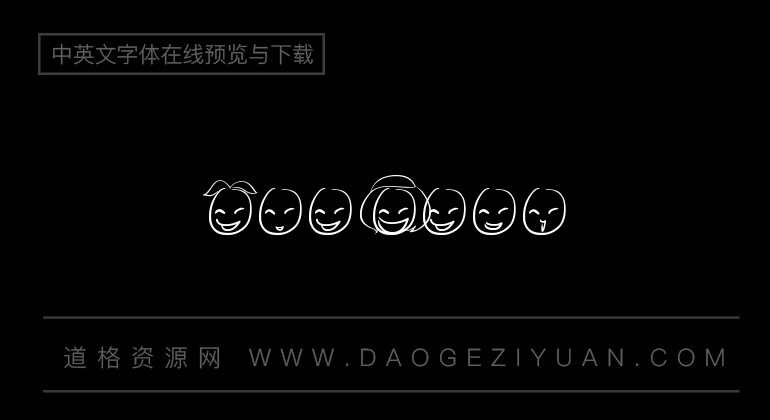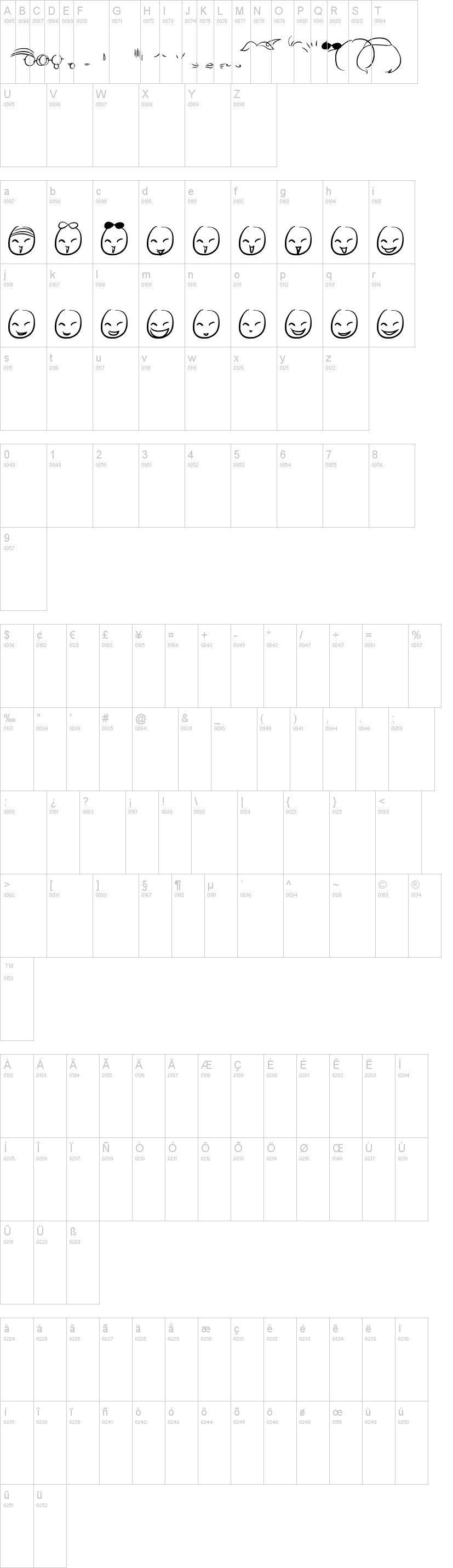
Mini Smile
Mini Smile是一款非常可爱的字体,它的字符非常圆润和柔和,给人一种温暖和友好的感觉。这个字体的特点是每个字母都有一个小小的笑脸表情符号,这也是它名字的来源。 Mini Smile字体非常适合用于制作卡通、儿童或者情感类的设计,例如儿童书籍、漫画、贺卡、广告宣传等。Mini Smile字体的特点是可爱、清新,非常容易吸引人们的注意力。
Mini Smile是一款非常不错的手写艺术字体,具有很好的视觉感,适合于文化类的宣传设计、商业类品牌的广告和产品包装设计以及个性化文字排版等较多场景。
Mini Smile字符映射图